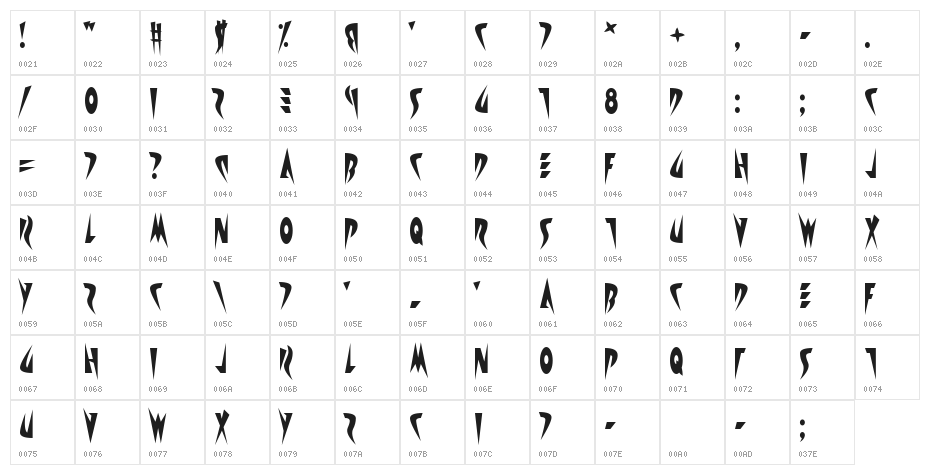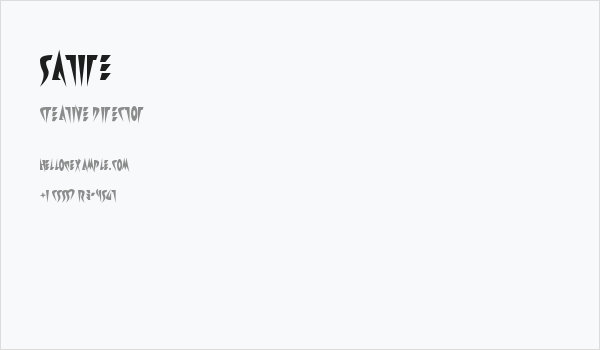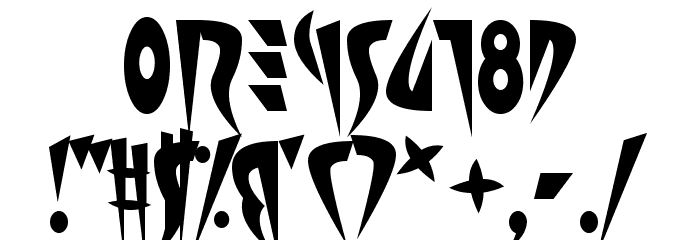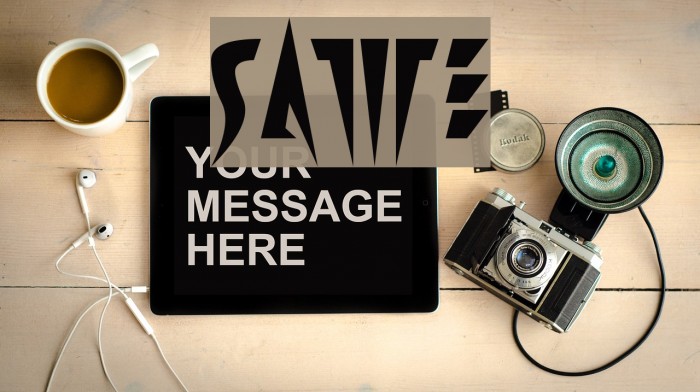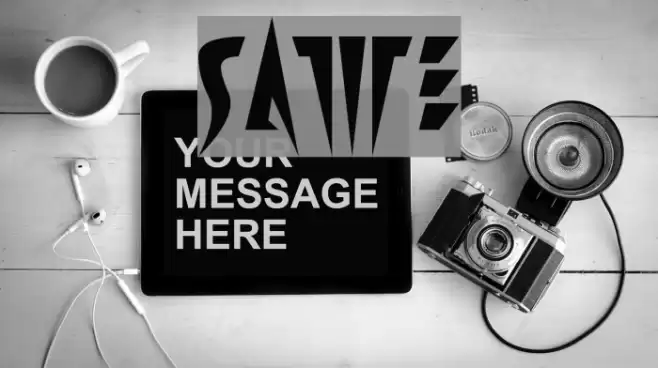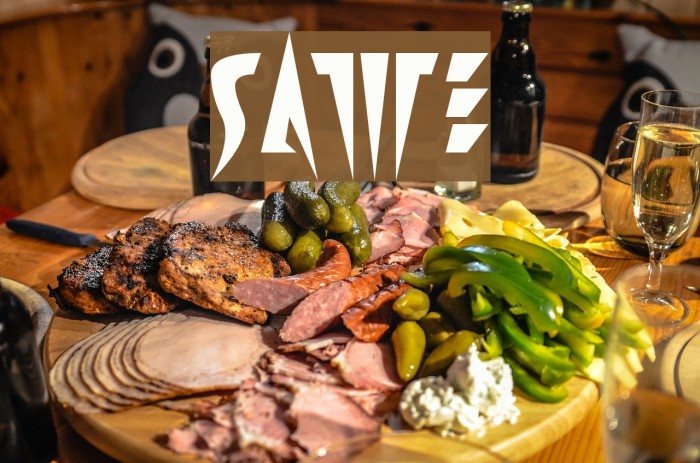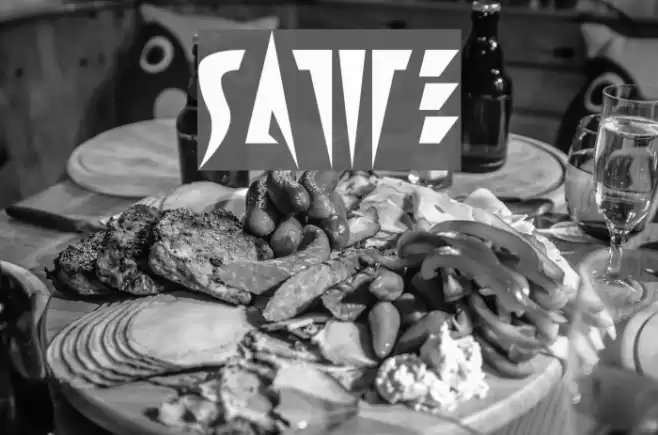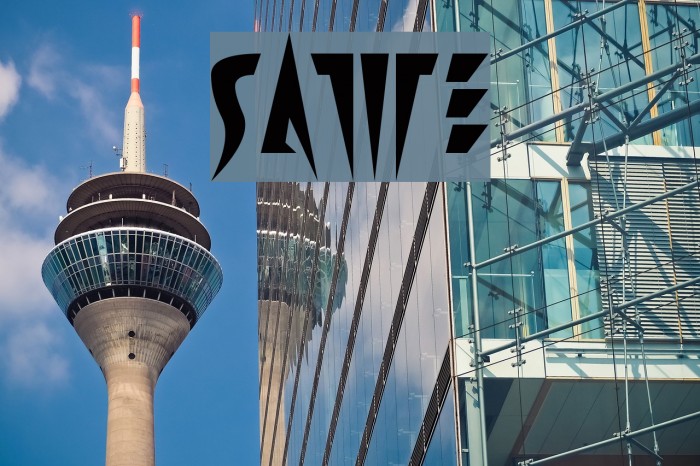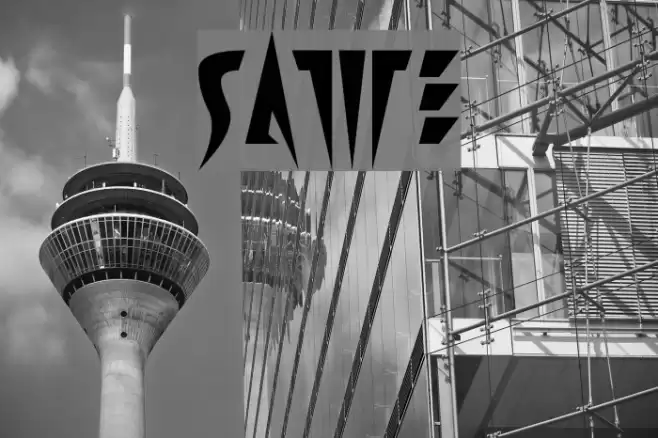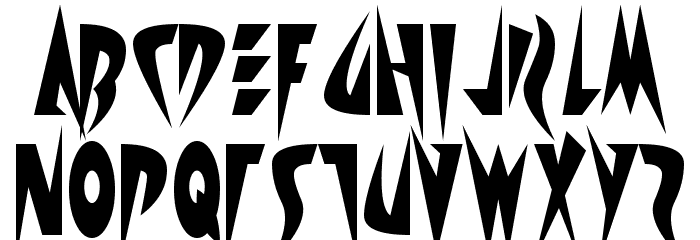
Satire Font
| Stil general | Modern, Edgy |
| Proiecte propuse | Ideal for album covers, posters, video game titles, and any project needing a bold, edgy aesthetic. |